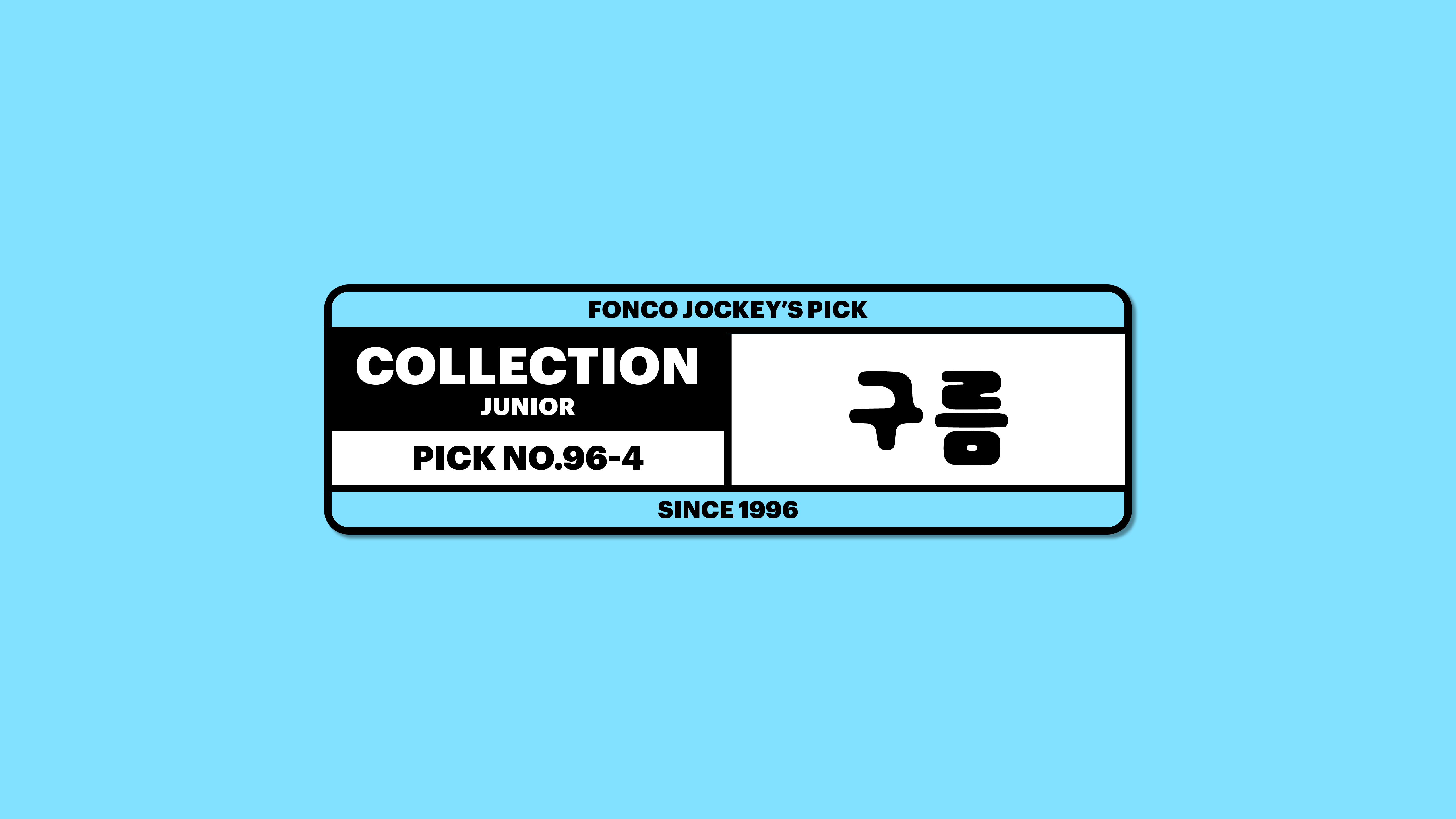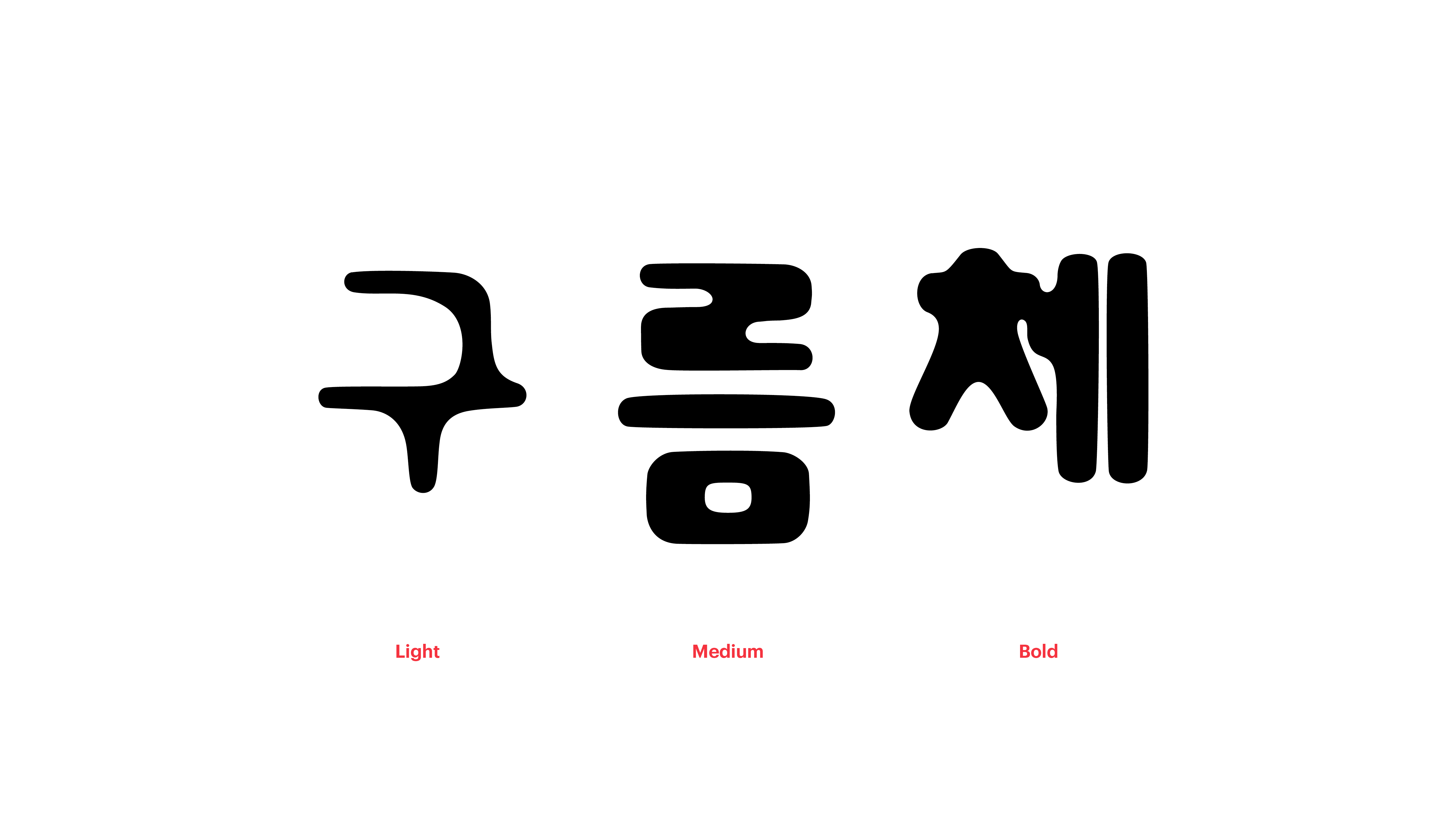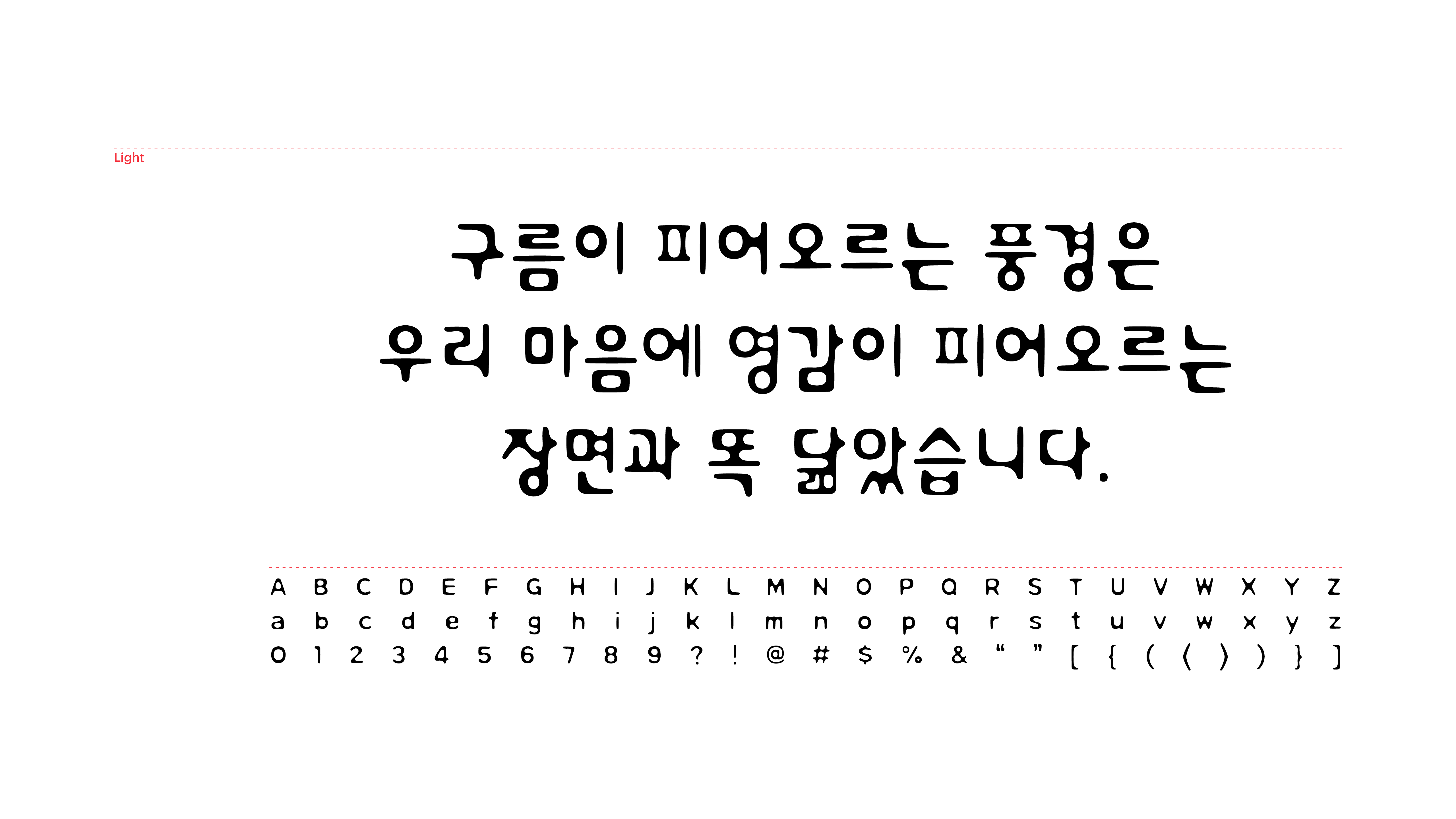
구름이 피어오르는 풍경은 우리 마음에 영감이 피어오르는 장면과 똑 닮았습니다. 몽실몽실 우리 마음에 떠오르는 자연스럽고 재미난 이야기들을 적고 싶을 때, 우연한 번짐의 속성을 그대로 살린 구름체에 손이 가는 이유이기도 하지요. 폰트가 지닌 유연한 곡선이 우리의 생각을 평소보다 더 먼 곳까지 데려갈 수 있다면, 우리의 상상은 곧 현실이 될지도 모를 일입니다.
Yoon 구름